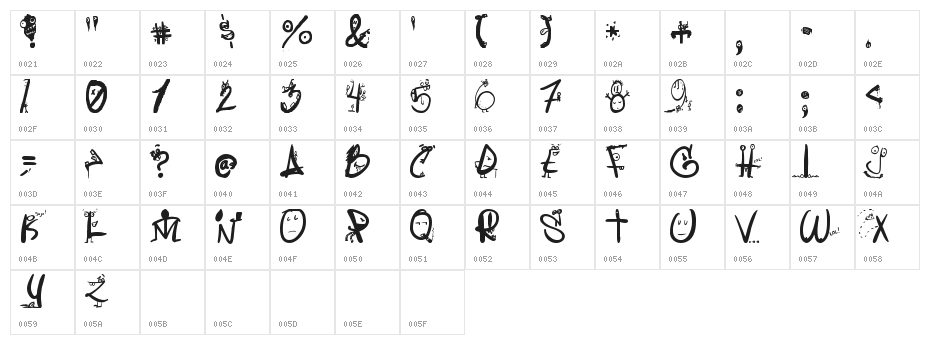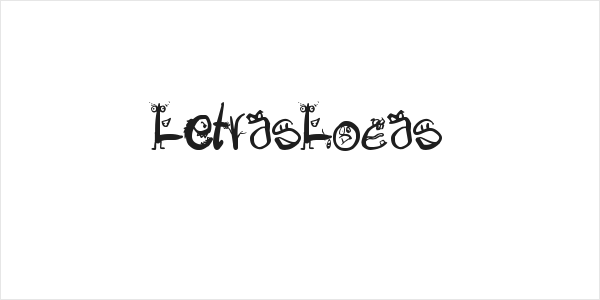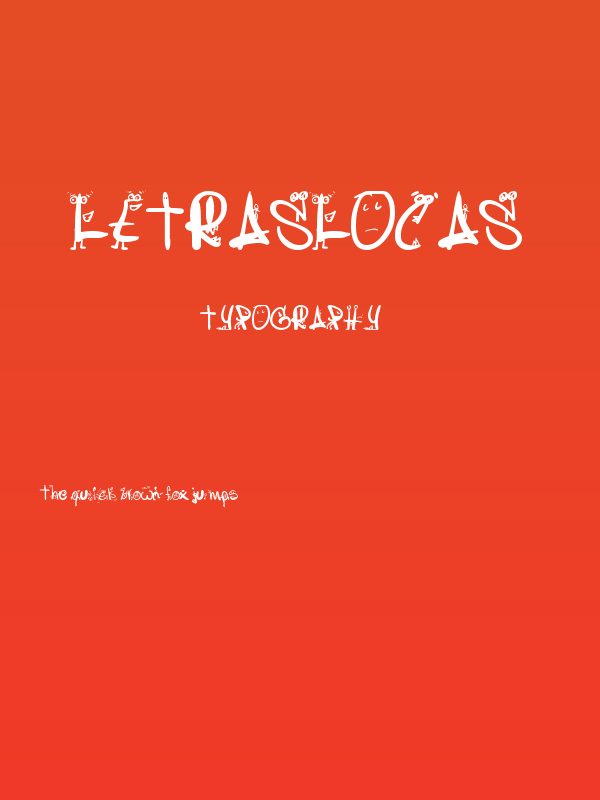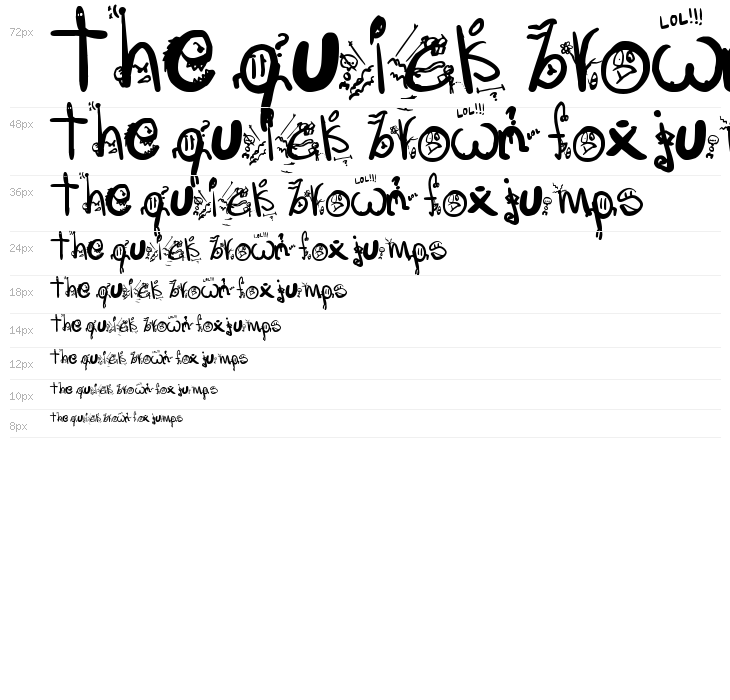
LetrasLocas Font
| Stile generale | Playful, Whimsical |
| Progetti proposti | Ideal for children's books, comic strips, playful branding, and informal invitations. |